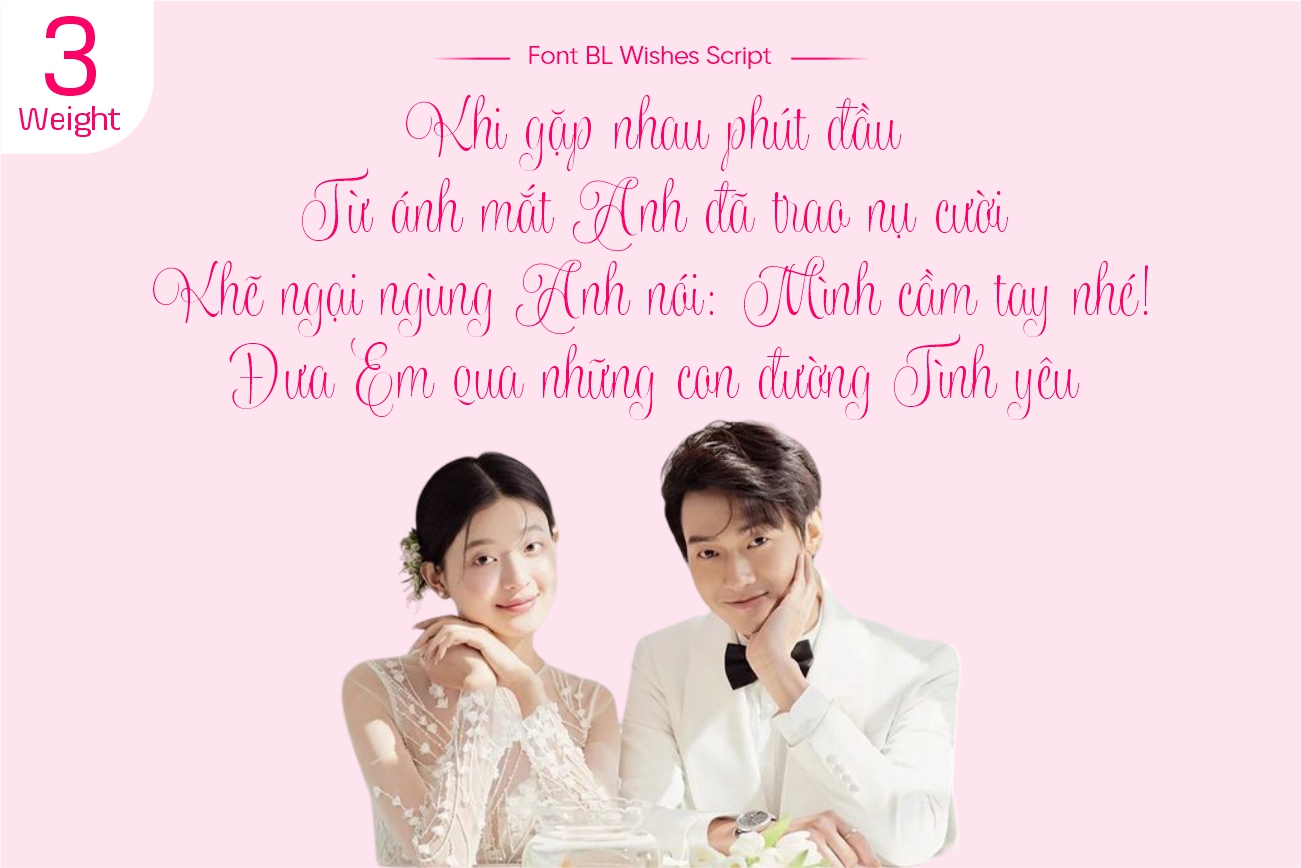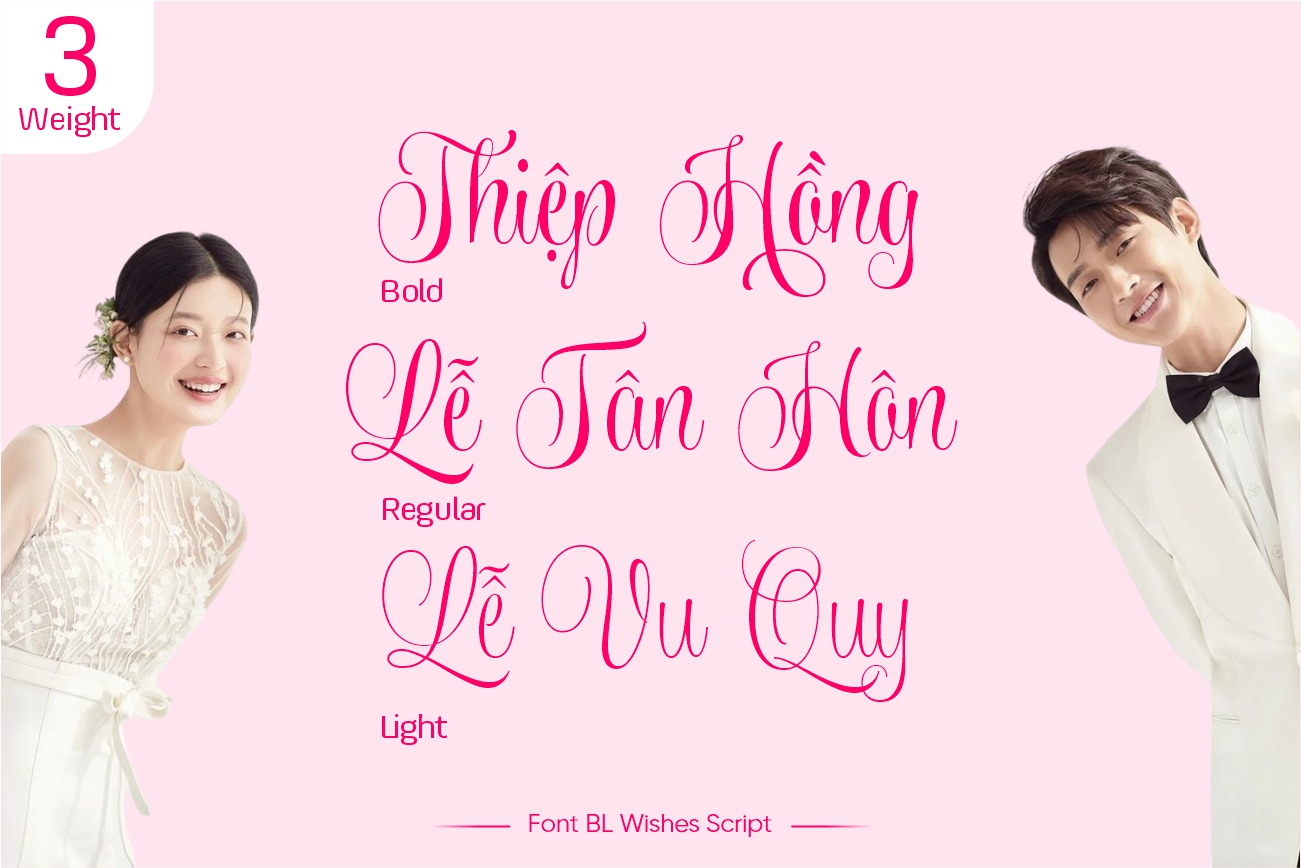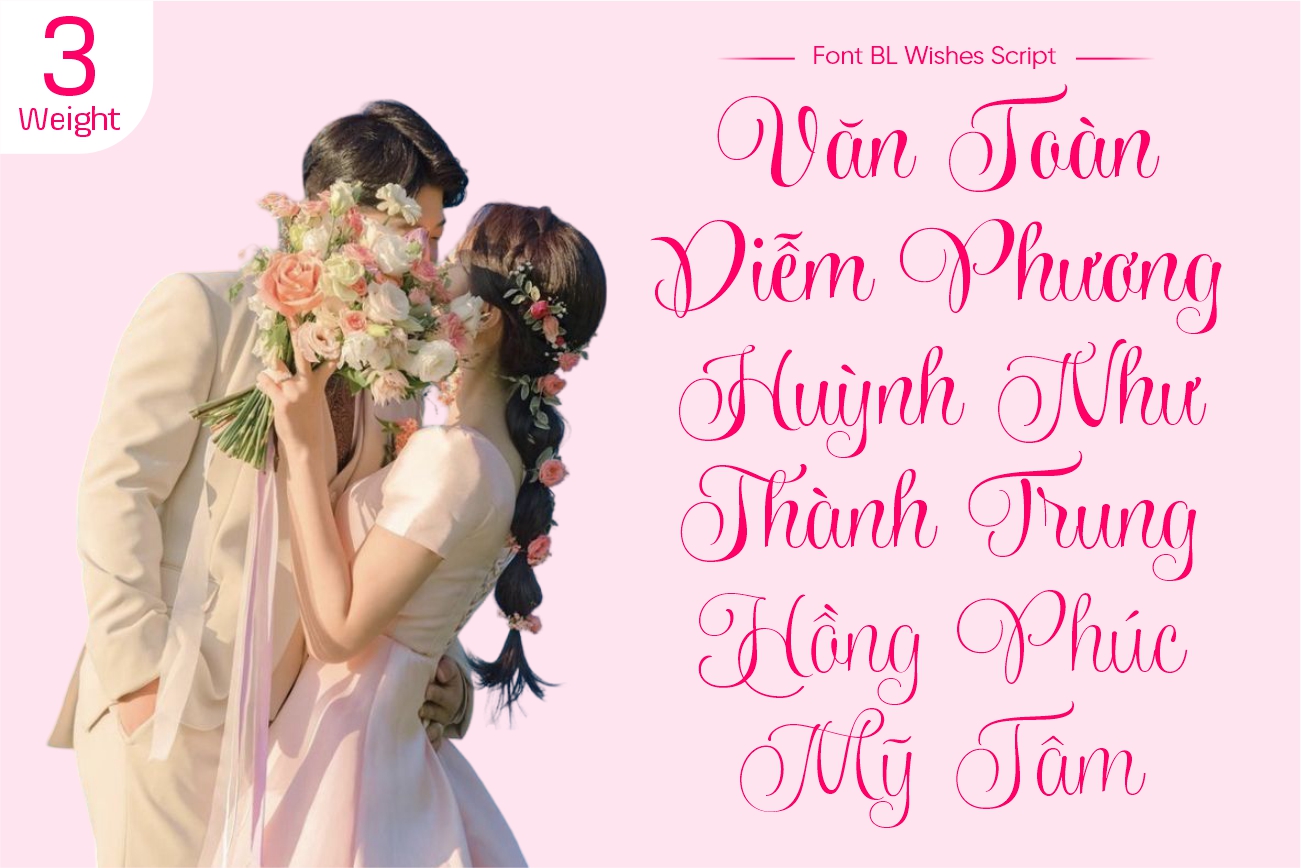
Bộ 3 font BL Wishes Script - Font thiệp cưới uyển chuyển
Giới thiệu font chữ BL Wishes
BL Wishes là một trong những font chữ script nổi bật dành cho các thiết kế mang tinh thần lãng mạn, nhẹ nhàng và giàu cảm xúc. Dựa trên nền tảng font Wishes do tác giả Hamilton thiết kế, Team BL đã Việt hóa hoàn chỉnh và đặt tên là BL Wishes, giúp font tương thích đầy đủ với tiếng Việt có dấu, phù hợp cho nhu cầu thiết kế trong nước, đặc biệt là các ấn phẩm cưới hỏi và sự kiện trang trọng.
Về kiểu dáng, BL Wishes thuộc nhóm font chữ uốn lượn với các nét cong mềm mại, liền mạch và có độ chuyển nét uyển chuyển tự nhiên như chữ viết tay cao cấp. Các ký tự được thiết kế chú trọng vào độ bay và nhịp điệu, tạo cảm giác thanh thoát nhưng vẫn rõ ràng, dễ đọc. Phần đầu và cuối chữ thường được kéo dài tinh tế, kết hợp với các vòng lượn lớn giúp tổng thể font mang vẻ sang trọng, phù hợp với những thiết kế cần nhấn mạnh cảm xúc và tính thẩm mỹ cao.
BL Wishes được xây dựng với 3 weight gồm Light, Regular và Bold, cho phép người dùng linh hoạt sử dụng trong nhiều bối cảnh khác nhau. Weight Light mang lại cảm giác mỏng nhẹ, tinh khôi, rất phù hợp cho các câu chúc, lời dẫn hoặc đoạn thơ ngắn. Regular là lựa chọn cân bằng, dễ ứng dụng trong thiệp cưới, banner hoặc poster. Bold tạo điểm nhấn rõ ràng, thích hợp cho tên cô dâu chú rể, tiêu đề hoặc các chi tiết cần thu hút ánh nhìn ngay từ đầu.
Là một font chữ cưới đúng nghĩa, BL Wishes thể hiện trọn vẹn tinh thần lãng mạn, hạnh phúc và trang nhã. Khi đặt trên nền ảnh cưới, phông màu pastel hoặc background tối giản, font vẫn giữ được độ nổi bật mà không làm mất đi sự mềm mại vốn có. Những câu chữ được thể hiện bằng BL Wishes thường gợi cảm giác ấm áp, gần gũi nhưng vẫn đủ tinh tế để phù hợp với các thiết kế mang tính kỷ niệm lâu dài.
Về nguồn gốc, việc Việt hóa từ font Wishes của Hamilton giúp BL Wishes thừa hưởng trọn vẹn tinh thần thiết kế ban đầu, đồng thời được tinh chỉnh lại hệ thống dấu tiếng Việt sao cho hài hòa với nét chữ, không gây rối hoặc nặng bố cục. Đây là điểm cộng lớn giúp BL Wishes trở thành font chữ script được nhiều nhà thiết kế Việt lựa chọn cho các dự án cưới, thiệp mời, photobook và branding mang phong cách lãng mạn.
Nhìn chung, BL Wishes là sự kết hợp hài hòa giữa tính nghệ thuật và khả năng ứng dụng thực tế. Nếu bạn đang tìm kiếm một font chữ uốn lượn đẹp, một font chữ script mềm mại hay một font chữ cưới tinh tế cho các thiết kế giàu cảm xúc, BL Wishes chắc chắn là lựa chọn đáng để trải nghiệm và sử dụng lâu dài.